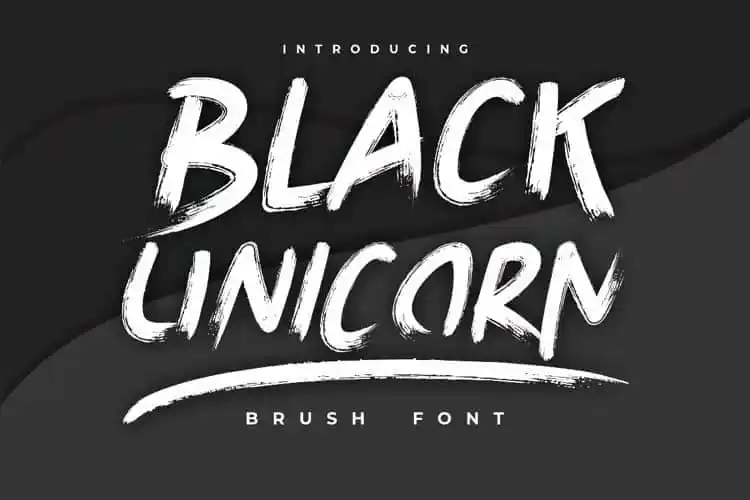
Black Unicorn Brush Font
A Black Unicorn Brush Font é uma escolha perfeita para quem busca um estilo script com personalidade e vibrância. Embora tenha características mais simples de outras fuentes similares, essa criação original de 99designs oferece uma textura única e autêntica que remete a pinturas à mão em álbabuca seca. Além dos detalhes únicos, como a imperfeição daquele único traço de caligrafia chamada baseline muito bouncando, essa fonte apresenta muitas alternativas de ligação e desenhos que dão vida real às suas escritas. Esses elementos adicionais permitem uma aparência que poderia ser facilmente confundida com a sua própria escrita criativa. Quer seja para projetos artísticos ou até mesmo para ilustrações, é difícil encontrar uma fonte tão versátil e convidativa quanto a Black Unicorn Brush Font. E o melhor? Você pode aceder aos swashes (ou traços extra) da fonte com facilidade – basta digitar o caractere sublinhado várias vezes. Se você está à procura de algo que dê vida às suas criações, esta fonte é certamente uma excelente opção. Com sua textura vibrante e detalhes únicos, a Black Unicorn Brush Font é certamente um complemento ideal para qualquer projeto criativo atual ou futuro.